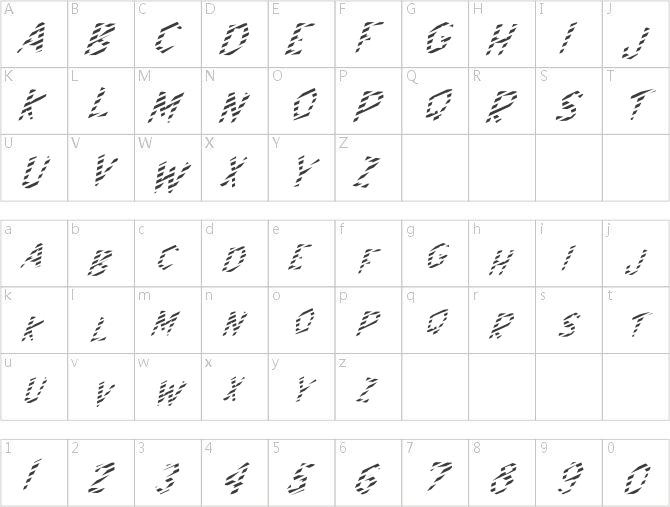
FZ JAZZY 8 STRIPED ITALIC
FZ JAZZY 8 STRIPED ITALIC介紹
FZ JAZZY 8 STRIPED ITALIC字體字庫是一款讓人賞心悅目、百看不厭的英文字體,適合各類廣告和產品包裝設計應用,字體大小0.04MB,格式為ttf字體,上傳用戶是誠澤永信,作者/版權方為未知
FZ JAZZY 8 STRIPED ITALIC效果圖